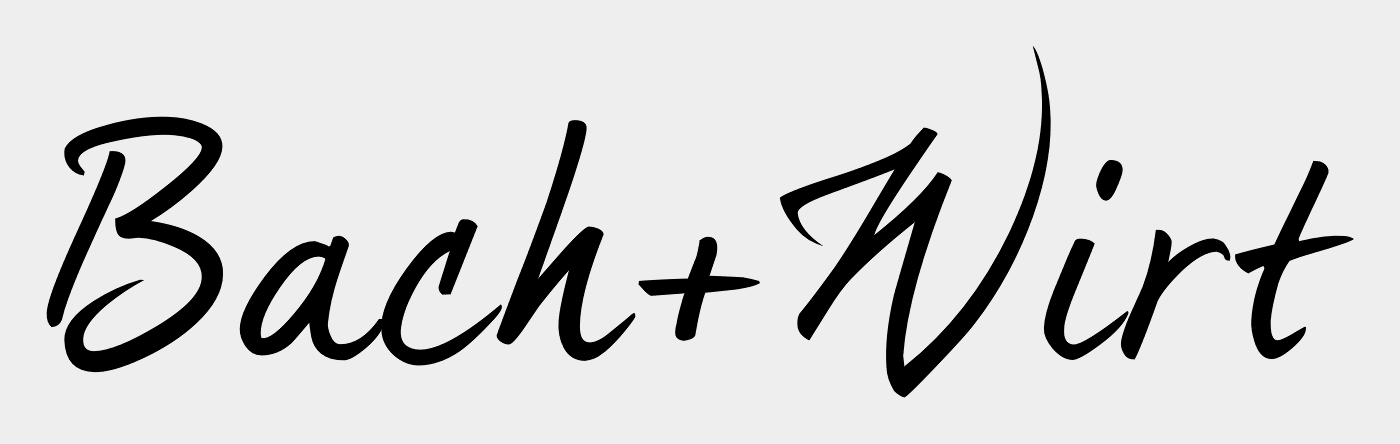
Suche diese Schriftart
ich suche dringend diese Schriftart auf dem Logo. Vielleicht kann
mir jemand helfen.
Dear Joe 5 Alternatives.
Das ist die Grundform:
Das "h" gibt es in dieser Form eventuell nicht und wurde dann wohl aus einem alternativen "k" (das hat diesen Schwung) erstellt.